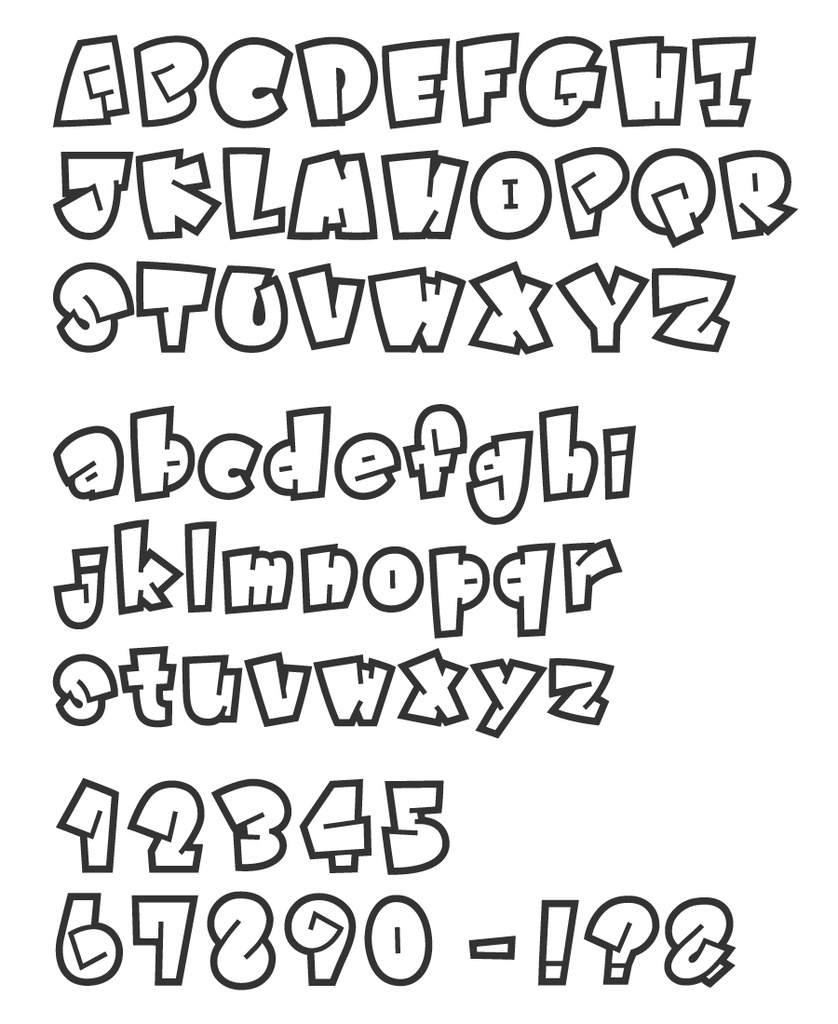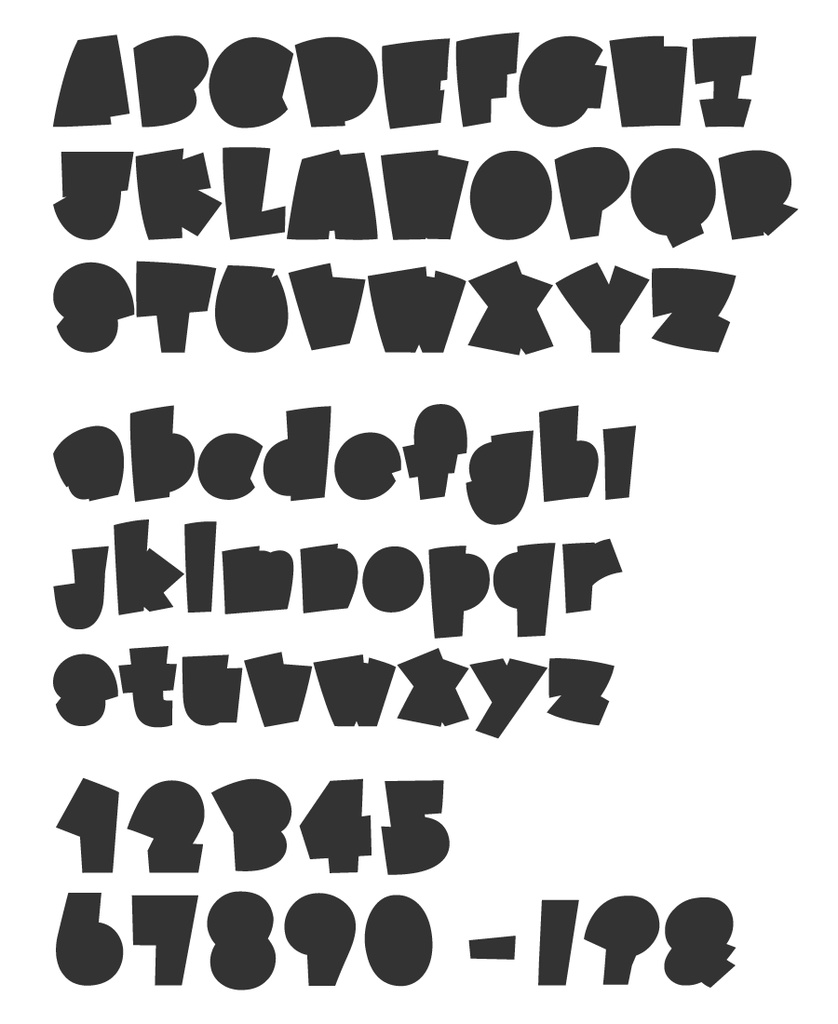
POOLBAG font (FULL)
●「POOLBAG」は以下の2ウェイトを収録しています。 ・outline…線 ・inside…塗り 組み合わせることで、塗りや影のようにアレンジすることができます。 ●こちらは商用利用可能なフルバージョンです。 お試しや個人利用をお考えの方は以下トライアル版もございます。 https://nomuraya.booth.pm/items/4174966 ●以下の利用規約を必ずお読みの上、ダウンロードください。 ーーーーーーーー ・できること OK ○印刷物、WEB、映像作品、配信等で使用すること ○ロゴマークとして使用すること ○当フォントを加工、変形して使用すること ○当フォントを利用してのグッズなどの制作 ※利用報告・クレジット表記不要 ・ご遠慮ください NG ×当フォントそのものを再配布したり販売すること ×当フォントファイルを加工し、再配布したり販売すること ×当フォントを使ったロゴマークの商標登録 ×誹謗中傷の目的での使用 ・その他 ※著作権は放棄しておりません。 ※利用条件は予告なく変更することがあります。 ※当フォントをダウンロード・インストール・使用した際に発生したあらゆる問題において当方の責任を負わないものとします。 ※スマートフォン、タブレットでのダウンロードについては動作確認等は行っておりません。 ーーーーーーーー